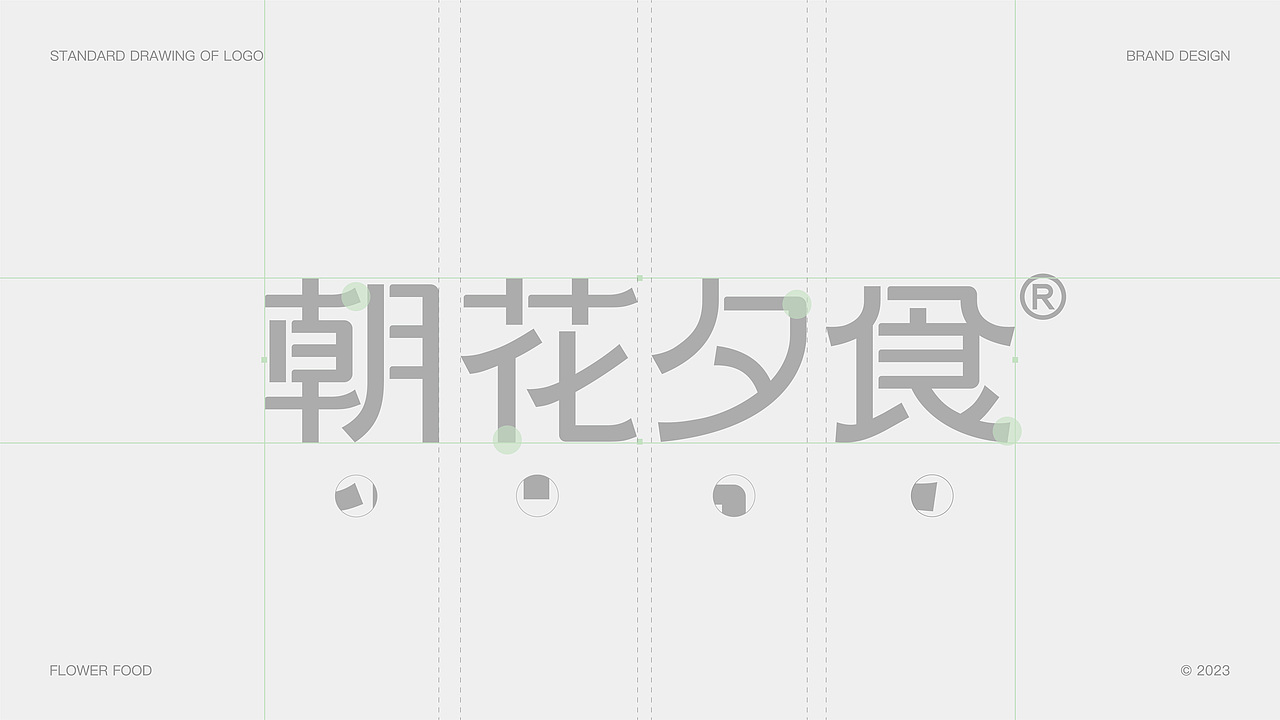
朝花夕食 | 品牌视觉设计
朝花夕食是一家以中式糕点和休闲茶饮为主的休闲空间。主理人希望打造一个全新的形象加强在年轻化群体中的传播力度,为此我们挑选出6种不同的代表性产品,并提取出“新鲜”、“休闲”、“好食”的概念,用于引起年轻群体的共鸣。在视觉表现上,提取口味花卉元素,并用新中式插画风格表现,既蕴含国风韵味,又不失创新精神。
Flower Food is a leisure space mainly featuring Chinese pastries and casual tea drinks. The manager hopes to create a brand new image and strengthen its dissemination among the younger group. Therefore, we have selected six different representative products and extracted the concepts of "fresh", "leisure", and "good food" to resonate with the younger group. In terms of visual expression, extract flavor floral elements and use the new Chinese style illustration style to express, which not only contains the charm of Chinese style, but also lacks the spirit of innovation.